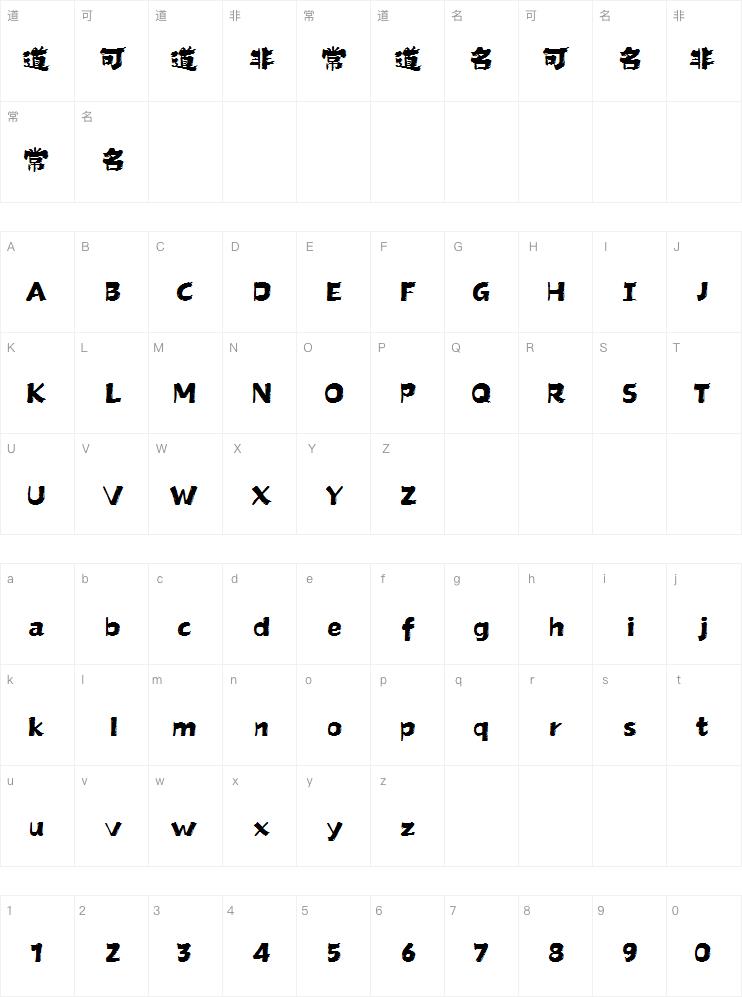
山海清野手书,是一款全新的毛笔风格的字体,包含汉字9169个,符号200+个。该字体笔画用笔轻松随性,粗细结合,结构多变灵动整体给人一种放松厚重的视觉效果。造型生动有趣,具有灵活的适用性;同时以毛笔风格的表现形式,使字体更别具一格,笔画的飞白效果使字体的气息更加流畅,笔画间的关系密不可分,同时也增加了字体的自由之感。